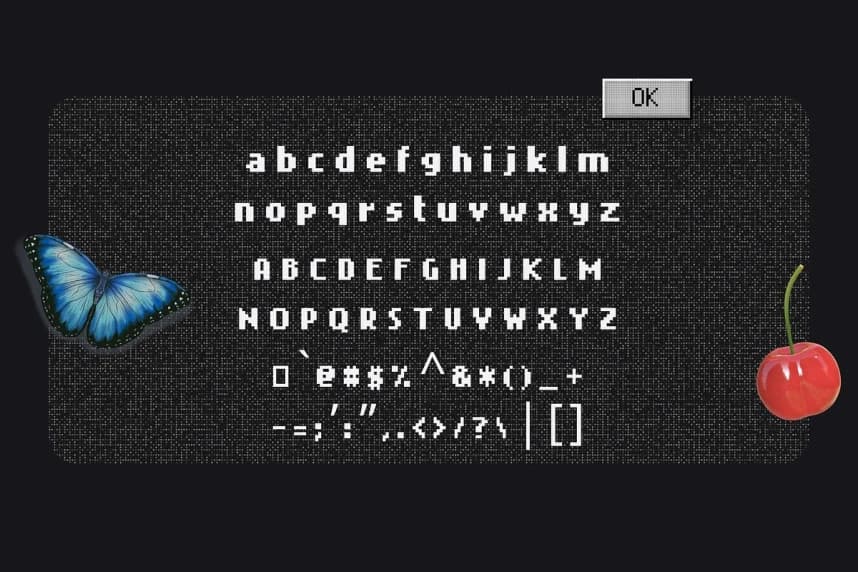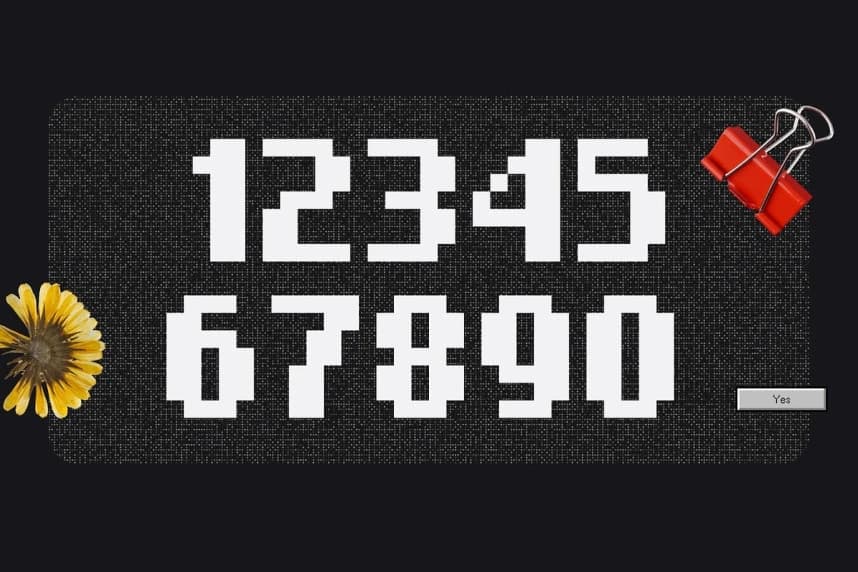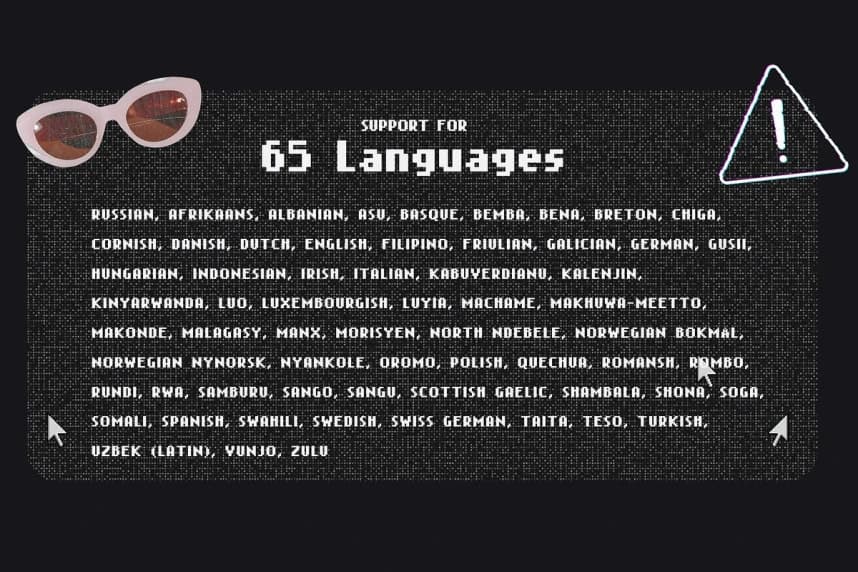
Digital 808 Yazı Tipi
Digital 808 Font, temiz ve çağdaş bir dokunuşa sahip retro estetiği seven yaratıcılar için tasarlanmış modern bir piksel yazı tipidir. Özenle tasarlanmış bu yazı tipi 249 glife sahiptir ve 63 dili destekler; bu da onu küresel tasarım projeleri için çok yönlü bir seçenek yapar.
Digital 808 Font, temiz ve çağdaş bir dokunuşla retro estetiği seven yaratıcılar için tasarlanmış modern bir piksel yazı tipidir. Özenle tasarlanmış bu yazı tipi 249 glif içerir ve 63 dili destekler, bu da onu küresel tasarım projeleri için çok yönlü bir tercih haline getirir.